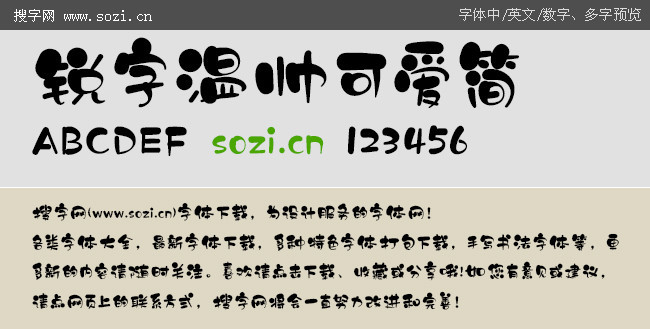
銳字溫帥可愛(ài)簡(jiǎn)
搜字網(wǎng)提供一款銳字溫帥可愛(ài)簡(jiǎn)中文字體下載,銳字溫帥可愛(ài)字體字形溫潤(rùn)飽滿(mǎn)、親切乖巧,筆畫(huà)不拘一格、粗細(xì)對(duì)比協(xié)調(diào)、簡(jiǎn)化變形有新意且不失識(shí)別性,營(yíng)造了一種輕松歡快、充滿(mǎn)趣味性的氛圍;非常適合兒童海報(bào),包裝設(shè)計(jì),網(wǎng)頁(yè)設(shè)計(jì)等設(shè)計(jì)使用。【本字體供個(gè)人非商業(yè)免費(fèi)使用,如需商用請(qǐng)聯(lián)系作者授權(quán)】